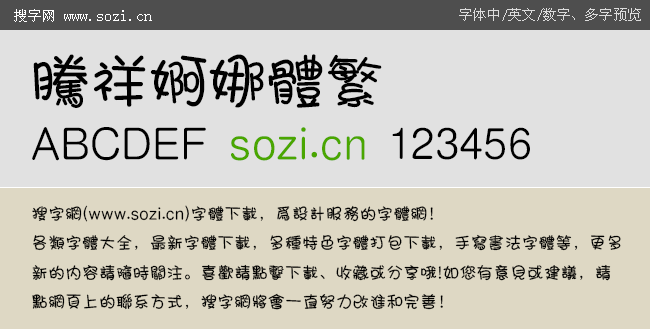
騰祥婀娜體繁
搜字網(wǎng)提供一款騰祥婀娜體繁中文藝術(shù)字體下載,騰祥婀娜體是一款設(shè)計(jì)精美,有著美好造型和姿態(tài)的騰祥字體,婀娜多姿如少女的形態(tài),童趣橫生給人舒適視覺(jué),整體效果非常的出色,且字庫(kù)完整,可用于印刷出版、包裝設(shè)計(jì)、廣告設(shè)計(jì)、網(wǎng)頁(yè)設(shè)計(jì)等。